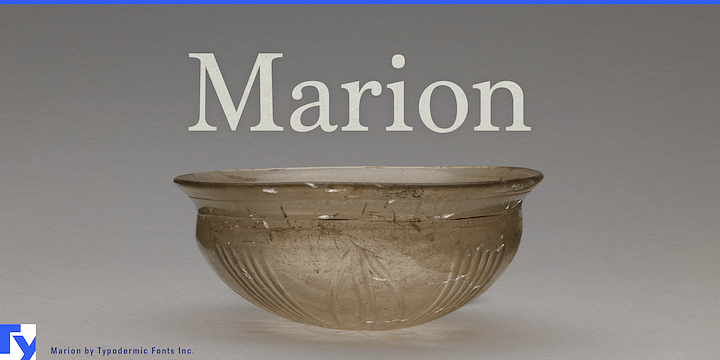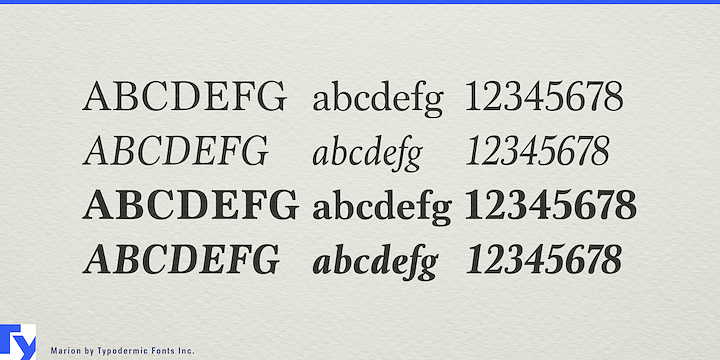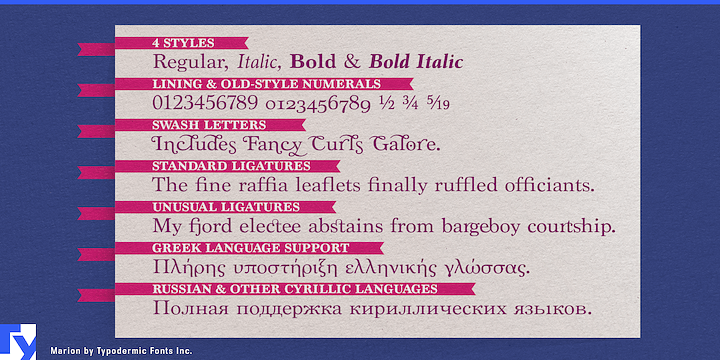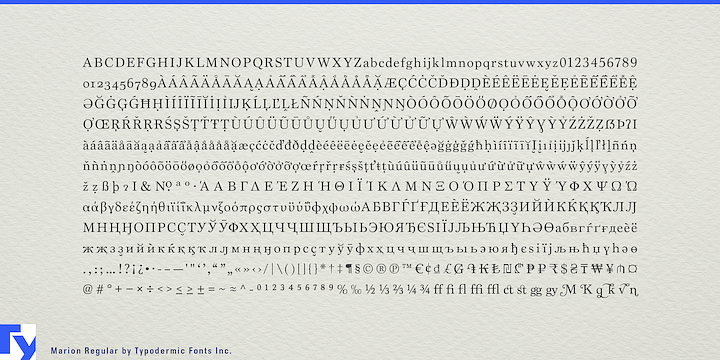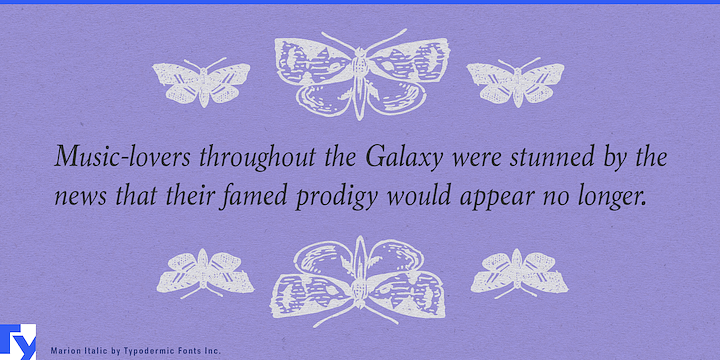
Treten Sie ein in die edle Welt von Marion, einer Übergangs-Serifenschrift, die mit müheloser Anmut die Kluft zwischen den Jahrhunderten überbrückt. Diese außergewöhnliche Schriftart ist nicht nur eine Hommage an die Vergangenheit – sie orchestriert eine typografische Symphonie, die die Echos der industriellen Revolution und das Geflüster literarischer Salons widerhallt.
Marions DNA ist eine meisterhafte Mischung aus Einflüssen, die die klassische Struktur von Century Roman mit der edlen Strichführung von Baskerville verbindet. Aber es sind die unverwechselbaren Hammerkrallen-Serifen, die die Schrift wirklich auszeichnen und jedem Buchstaben den robusten Geist der Innovation des 19. Jahrhunderts verleihen. Diese einzigartigen Serifen rufen das Bild dampfbetriebener Präzision hervor, als wäre jeder Buchstabe im Herzen einer viktorianischen Gießerei geschmiedet worden. Marion ist in den Schrifttypen Regular, Italic, Bold und Bold Italic erhältlich und bietet ein Quartett an Stimmen, die jede Design-Vision zum Ausdruck bringen können. Von der dezenten Eleganz der Regular-Stärke bis zur imposanten Präsenz der Bold-Stärke behält jede Variante Marions Kernidentität bei – eine perfekte Balance aus historischer Würde und zeitgenössischer Finesse.
Marion spricht nicht nur zur Vergangenheit, sie kommuniziert mit ihr. Die Mediävalziffern und Standard-f-Ligaturen sorgen dafür, dass Ihr Text nicht nur authentisch aussieht, sondern sich auch mit der flüssigen Anmut eines gut geschriebenen Romans liest. Wenn Ihr Design nach einem Hauch von Verspieltheit verlangt, stehen Marions exzentrische, optionale Ligaturen und fröhliche Schwungbuchstaben bereit, um ihm eine persönliche Note zu verleihen. Im Bereich Branding und Editorial Design ist Marion die unübertroffene Größe. Stellen Sie sich vor, diese Schriftart ziert die Seiten eines luxuriösen Bildbandes, verleiht dem Impressum einer angesehenen Zeitschrift Würde oder gibt dem Etikett einer Craft-Brauerei einen Hauch von Industrie-Chic. Ihre einzigartige Mischung aus historischem Reiz und modernem Feingefühl macht sie zur idealen Wahl für jede Marke, die sowohl Tradition als auch Innovation vermitteln möchte.
Marions sprachliche Vielseitigkeit ist ebenso beeindruckend wie ihre Design-Herkunft. Sie unterstützt eine große Palette lateinischer europäischer Sprachen, Vietnamesisch, Griechisch und die meisten kyrillischen Schriftsysteme und sorgt dafür, dass Ihre Botschaft mit der gleichen Klarheit und Eleganz ankommt, egal ob Sie sich an ein Publikum in Paris oder St. Petersburg, Athen oder Hanoi wenden. Jede Sprache findet ihre Stimme in Marions sorgfältig gestalteten Zeichen, die jeden Absatz in eine Hommage an das typografische Erbe verwandeln. Gestalten Sie nicht nur – kuratieren Sie mit Marion ein typografisches Erlebnis. Machen Sie diese Schriftart zum Eckpfeiler von Kreationen, die nicht nur kommunizieren, sondern die Leser in eine Ära industrieller Wunder und literarischer Giganten versetzen.